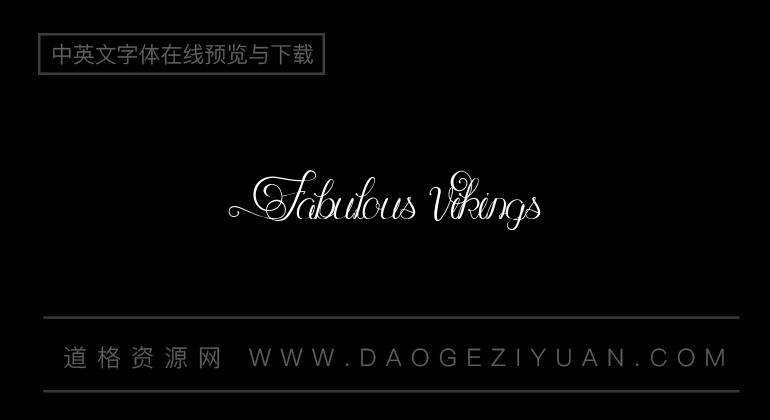
Fabulous Vikings
? Fabulous Vikings 字体是一款复古风格的字体,它采用古老的拉丁文字体框架,以及清新的形状和细节,给人以强烈的历史感。它的字形充满活力,拥有深厚的传统感,具有浓厚的古典气息,可以用于多种不同的设计项目,比如海报、标志、标题等等。
Fabulous Vikings是一款非常不错的手写艺术字体,具有很好的视觉感,适合于文化类的宣传设计、商业类品牌的广告和产品包装设计以及个性化文字排版等较多场景。